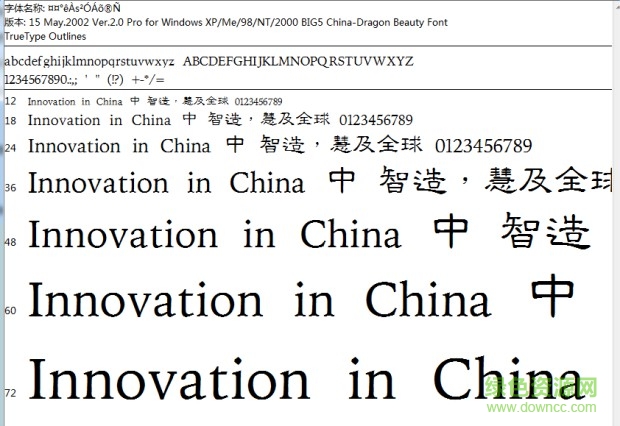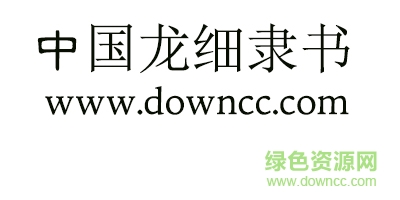
中國(guó)龍細(xì)隸書(shū)字體是一款中國(guó)龍字體庫(kù)的細(xì)隸字體,這款字體可以在win7、win8、xp以及win10系統(tǒng)上安裝使用。中國(guó)龍細(xì)隸書(shū)字體超炫非常適合于美工設(shè)計(jì)。有喜歡的朋友可以來(lái)綠色資源網(wǎng)下載使用!
字形扁方左右分展
隸字一反篆字縱向取勢(shì)的常態(tài),而改以橫向(左右)取勢(shì),造成字形尚扁方,筆畫(huà)收縮縱向筆勢(shì)而強(qiáng)化橫向分展。
化圓為方化弧為直
這是隸書(shū)簡(jiǎn)化篆書(shū)的兩條基本路子。不過(guò)如果不了解篆書(shū)的圓,就不易掌握好隸書(shū)的方。因?yàn)殡`筆中的直畫(huà)或方折,還無(wú)不包藏著篆字的弧勢(shì),所以隸筆的直往往有明顯的波動(dòng)性,富于生命力。實(shí)際上隸書(shū)的筆意,是建立在筆畫(huà)運(yùn)動(dòng)方式基礎(chǔ)上的。
隸書(shū),有秦隸、漢隸等,一般認(rèn)為由篆書(shū)發(fā)展而來(lái),字形多呈寬扁,橫畫(huà)長(zhǎng)而豎畫(huà)短,講究“蠶頭雁尾”、“一波三折”。根據(jù)出土簡(jiǎn)牘,隸書(shū)始創(chuàng)于秦朝,傳說(shuō)程邈作隸,漢隸在東漢時(shí)期達(dá)到頂峰,上承篆書(shū)傳統(tǒng),下開(kāi)魏晉、南北朝,對(duì)后世書(shū)法有不可小覷的影響,書(shū)法界有“漢隸唐楷”之稱。